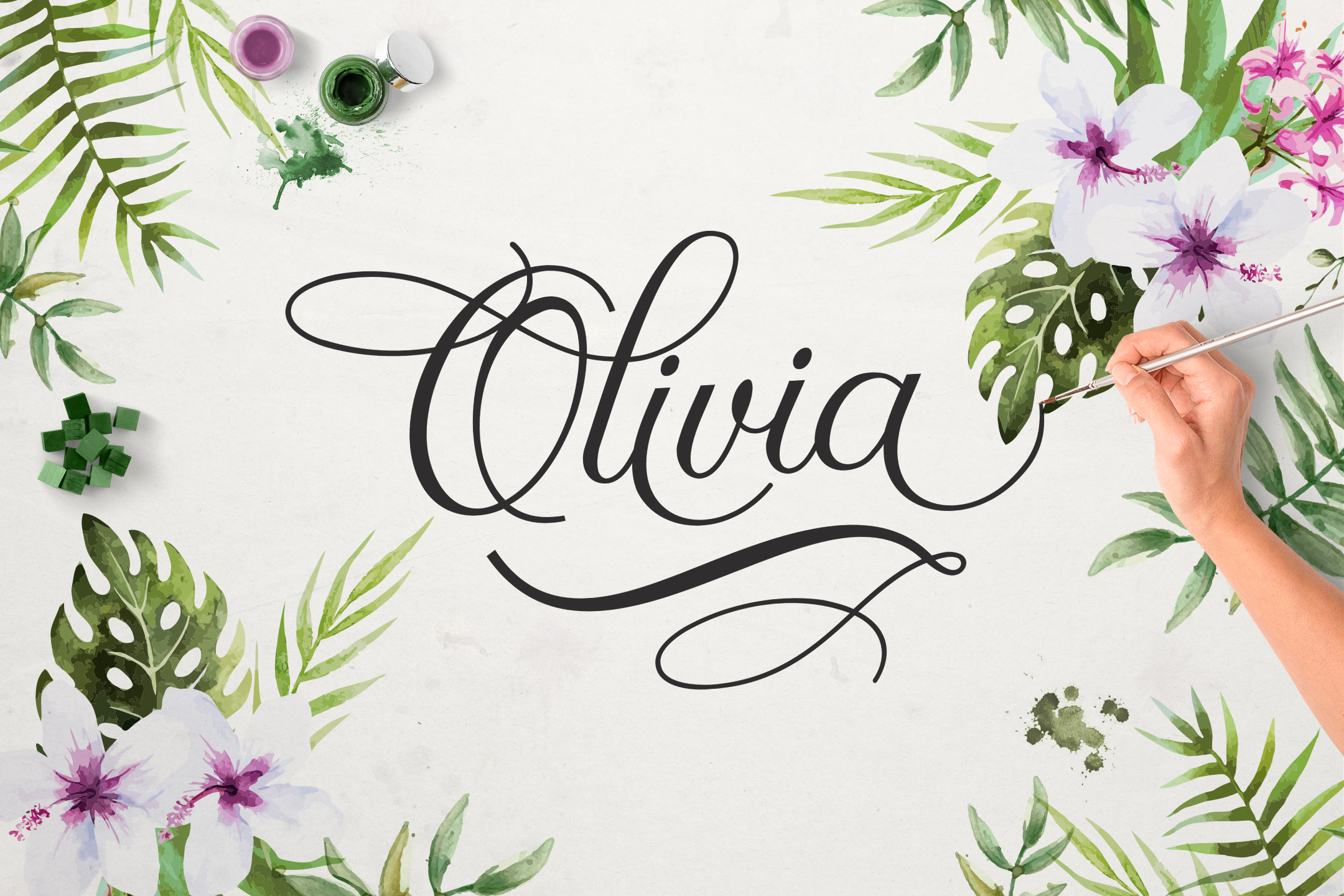
Olivia – Phông chữ Modern Script, phù hợp với mọi dự án như logo, dự án xây dựng thương hiệu, thiết kế đồ gia dụng, bao bì sản phẩm, cốc, trích dẫn, áp phích, túi mua sắm, áo phông, bìa sách, danh thiếp, thiệp mời, thiệp chúc mừng, nhãn, nhiếp ảnh, hình mờ, sự kiện đặc biệt và tất cả các dự án sang trọng khác cần có dấu ấn cao cấp.